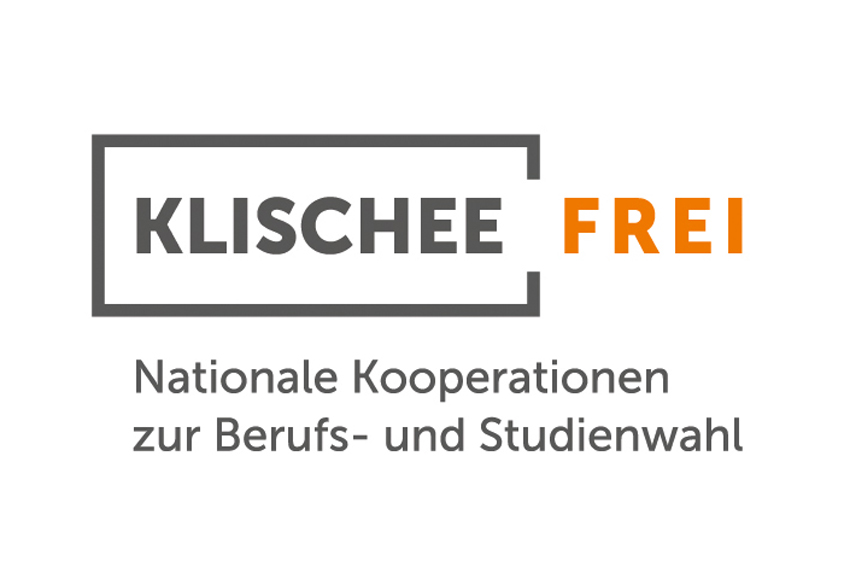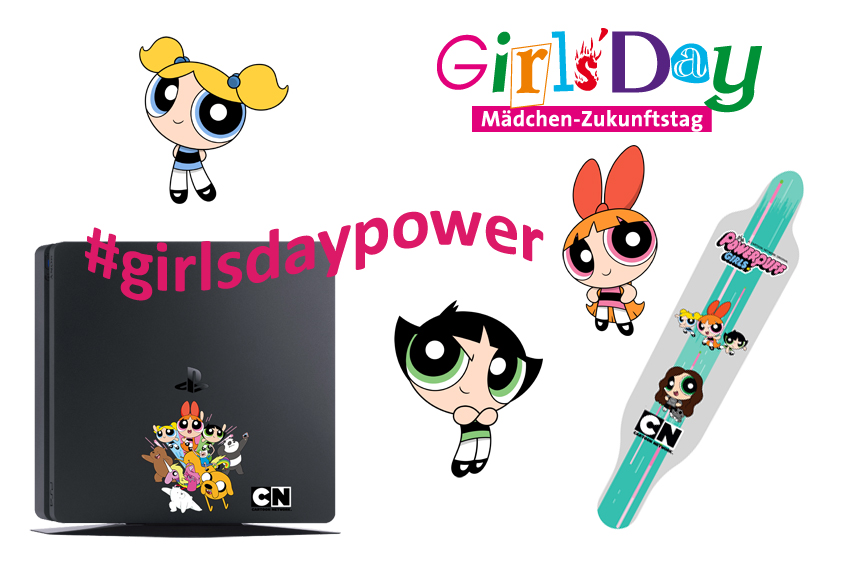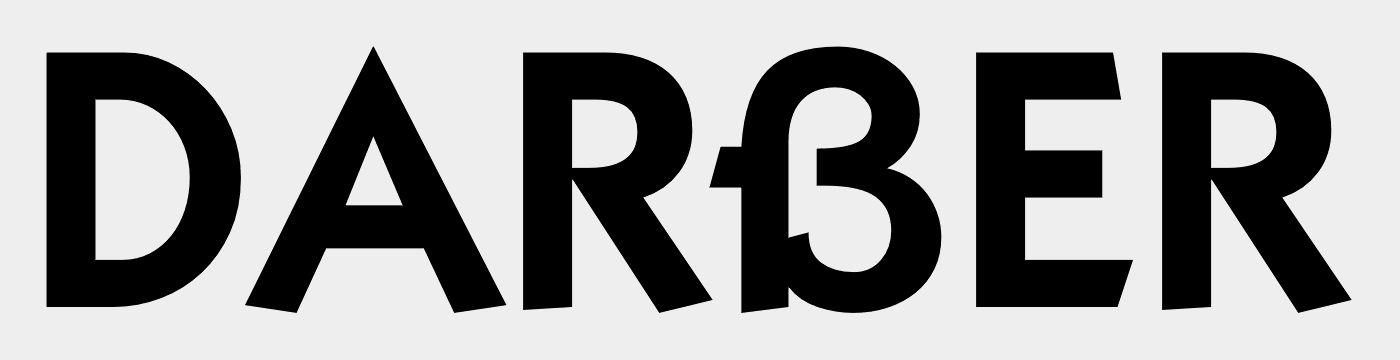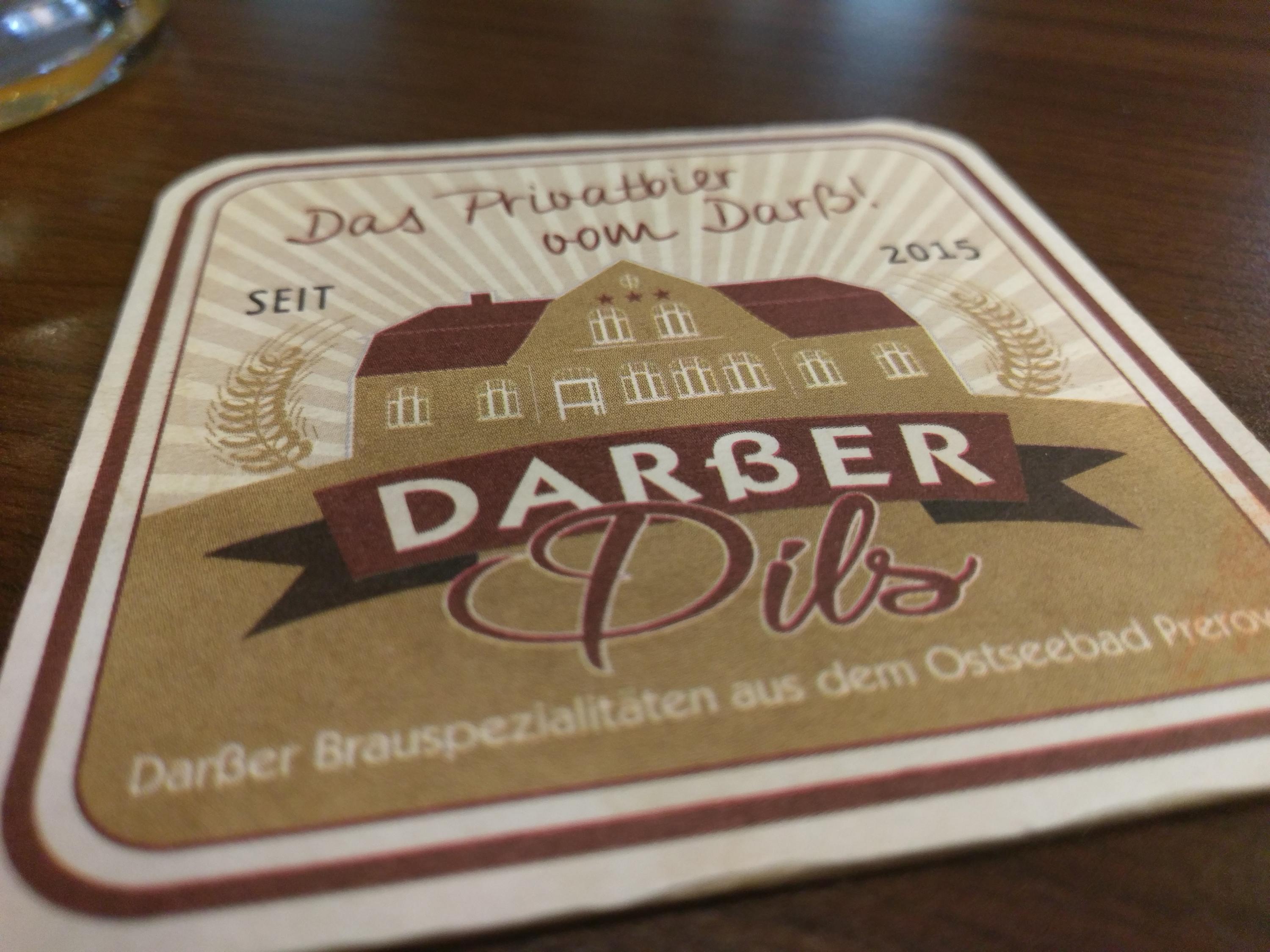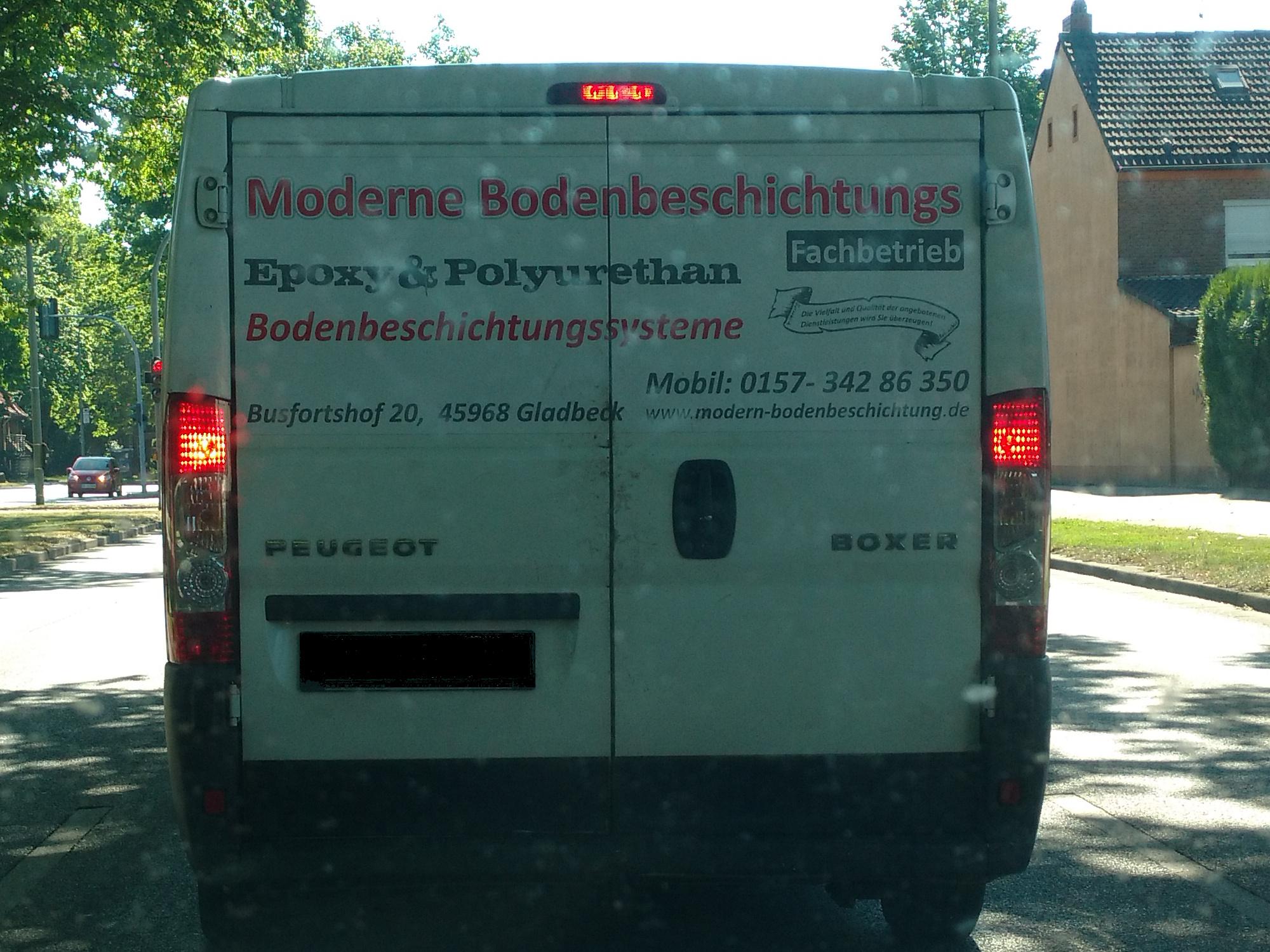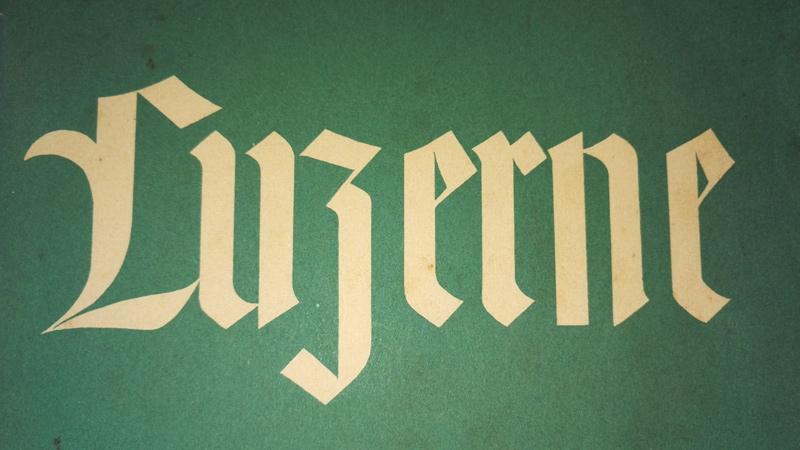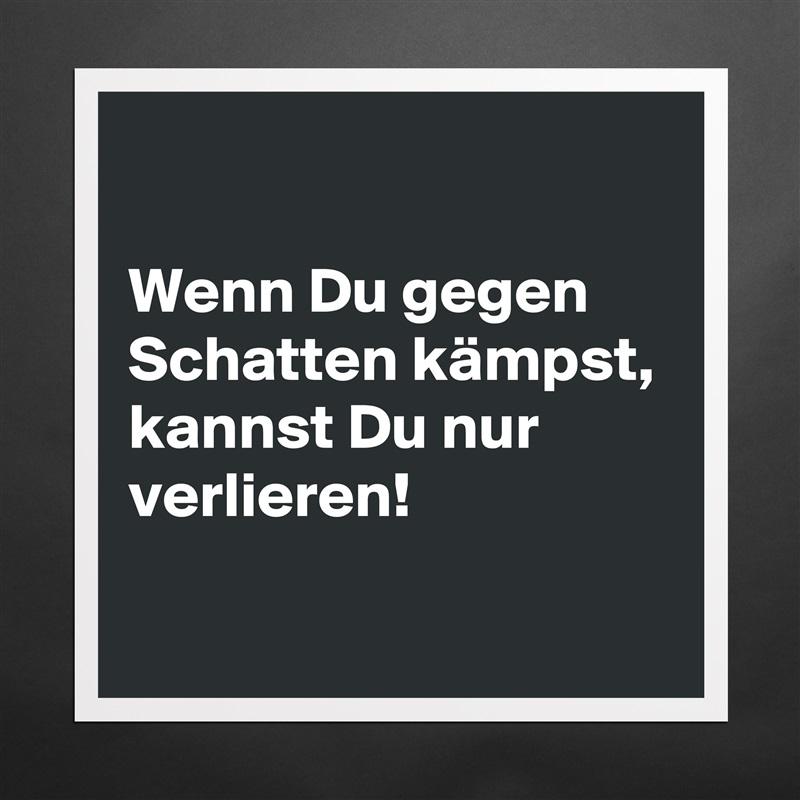
Wieso? Passt doch alles! Serifen, Kursive und schön dünn sind Mädchenkram. Jungs sind stark. Große Mädchenaugen sind niedlich. Große Jungsaugen sind Homer Simpson. Nur das Magenta ist mir ein Spur zu kräftig. So Telekom-mäßig. Hätte es ein zarteres Rosa nicht auch getan? :-?
KLISCHEE  FREI bedeutet doch wohl. dass man die Klischees für die eigenen Girls' Day oder  Boys' Day  - Akltionen frei bekommt?
Girls' Day? wird hier grad ein neuer Deppenapostroph eingeführt? Nach der Regel würde es kompliziert mit
Andreas' Day
Das ist der ganz normale englischsprachige Genitiv-Plural-Apostroph.
Das Versal-Ezett finde ich deutlich genug, aber das P ist "grenzwertig" für mein Auge.
Darber Dils!
Da darbt der ẞ-affine Darßbesucher! :trost:
Dirk Niebel, Oberfeldwebel der Reserve, früher Bundesminister, heute Lobbyist beim Rüstungskonzern Rheinmetall, publiziert dieses grausige Bild erst als Profilbild auf seiner Facebookseite, dann als einfache Bildveröffentlichung.
18403626_1667711903242935_84139046353801»Klagt nicht, Kämpst«
Goethe meinte sicherlich keinen solchen Analphabetismus in unbeholfenem Geschmiere gotischer Lettern, als er postulierte: »Die größten Vorteile im Leben überhaupt wie in der Gesellschaft hat ein gebildeter Soldat.«
Was erwartest du von jemandem, der mob-beordert ist?
Wenn du gegen den Strich kämmst, kannst du auch nur verlieren ;-) …
Nun ja, "kämpst" ist halt Plattdeutsch...
Aber nicht in der zweiten Person Plural.
Außerdem ist das eh Denglisch: Klagt nicht, campt! Wer im Niebel campt, sollte sich einen Teppich ins Zelt legen.
Habe ich bei den Unterlagen meines Opas gefunden. Er war Landwirt.
Es ist das Cover eines kleinen (ca. A5) Heftchens, in dem es wohl
um Infos zu besagter Pflanze geht ... mir hat die Schrift + Farbe
und der vergilbte / alte Touch (der hier nicht so rüberkommt)
sehr gut gefallen.
Die technischen Gegebenheiten des Bildes bitte ich zu entschuldigen, es ist mit der Telefonkamera auf die Schnelle aus einem fahrenden Auto entstanden.
Mußte ich machen, weil ich von dem Motto im Spruchband so beeindruckt war:
„Die Vielfalt und Qualität der angebotenen Dienstleistungen wird Sie überzeugen!“